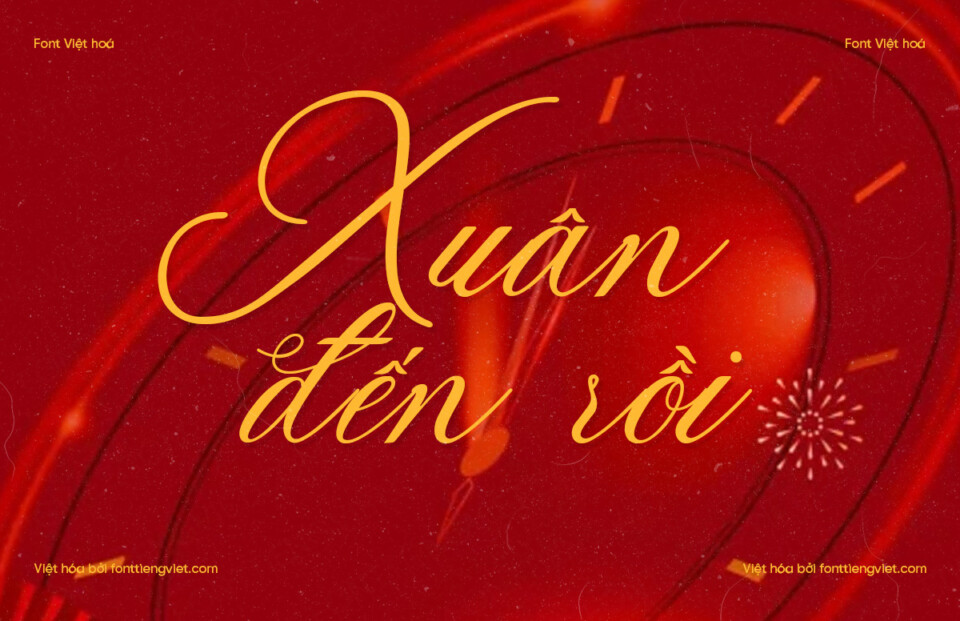
Font Việt hóa 1FTV VIP Romance Romantic – Font tết
Giới thiệu về Font Việt hóa 1FTV VIP Romance Romantic – Font tết
Trong thế giới thiết kế đồ họa hiện đại, việc tìm kiếm một bộ Font Miễn Phí chất lượng cao luôn là ưu tiên hàng đầu của các designer. Đặc biệt khi không khí xuân đang về, bộ Font Việt hóa 1FTV VIP Romance Romantic – Font tết nổi lên như một lựa chọn hoàn hảo để truyền tải thông điệp yêu thương. Đây là font chữ mang phong cách bay bổng, kết hợp hài hòa giữa nét cổ điển lãng mạn và sự hiện đại tinh tế. Với đường nét thanh mảnh nhưng chắc chắn, bộ font này không chỉ phù hợp cho các chủ đề tình yêu mà còn cực kỳ ấn tượng khi ứng dụng vào các ấn phẩm chúc mừng năm mới tại Việt Nam. Sự chỉn chu trong từng nét chữ giúp người dùng dễ dàng tạo nên những tác phẩm nghệ thuật có chiều sâu và sức hút thị giác mạnh mẽ.
Đặc điểm nổi bật của Font Việt hóa 1FTV VIP Romance Romantic – Font tết
Bộ Font Việt hóa 1FTV VIP Romance Romantic – Font tết sở hữu hệ thống ký tự đa dạng với các đường uốn lượn đặc trưng. Điểm mạnh lớn nhất của nó chính là khả năng hiển thị tiếng Việt hoàn hảo, không bị lỗi dấu – một vấn đề thường gặp ở các font ngoại nhập. Các nghệ nhân font chữ đã tinh chỉnh tỉ mỉ để các dấu thanh như huyền, sắc, hỏi, ngã, nặng được đặt ở vị trí cân đối, giữ nguyên linh hồn của bảng chữ cái Latinh nhưng vẫn đậm chất Việt. Bên cạnh đó, các ký tự thay thế (alternates) và chữ nối (ligatures) phong phú giúp bạn thỏa sức sáng tạo những tiêu đề độc bản, biến những dòng chữ đơn thuần trở thành những nhành hoa xuân rực rỡ trên trang giấy hoặc màn hình kỹ thuật số.
Ứng dụng Font Việt hóa 1FTV VIP Romance Romantic – Font tết trong thiết kế
Sự đa năng là yếu tố giúp Font Việt hóa 1FTV VIP Romance Romantic – Font tết chiếm trọn cảm tình của cộng đồng sáng tạo. Bạn có thể sử dụng font này cho nhiều mục đích khác nhau, từ thiệp mời đám cưới đến băng rôn sự kiện.
Thiết kế thiệp chúc mừng và lì bao lì xì
Vào dịp Tết Nguyên Đán, nhu cầu thiết kế bao lì xì và thiệp chúc Tết tăng cao. Sử dụng Font Việt hóa 1FTV VIP Romance Romantic – Font tết cho các câu đối hoặc lời chúc giúp sản phẩm trở nên sang trọng và ấm áp hơn. Những nét chữ mềm mại như lời tâm tình, mang lại cảm giác may mắn và thịnh vượng cho người nhận. Đặc biệt, khi kết hợp với tông màu đỏ hoặc vàng truyền thống, bộ font này tạo nên một tổng thể thị giác vô cùng hài hòa và đậm đà bản sắc dân tộc.
Trang trí ảnh truyền thông mạng xã hội
Đối với các bạn trẻ yêu thích việc sống ảo hoặc các chủ shop online, việc chèn chữ vào ảnh quảng cáo là rất quan trọng. Font chữ này giúp các banner khuyến mãi hay ảnh bìa Facebook trở nên chuyên nghiệp hơn. Nó không quá cứng nhắc như các font không chân thông thường mà mang lại cảm giác gần gũi, thân thiện, dễ dàng thu hút sự chú ý của khách hàng ngay từ cái nhìn đầu tiên.
Kết luận về bộ Font Việt hóa 1FTV VIP Romance Romantic – Font tết